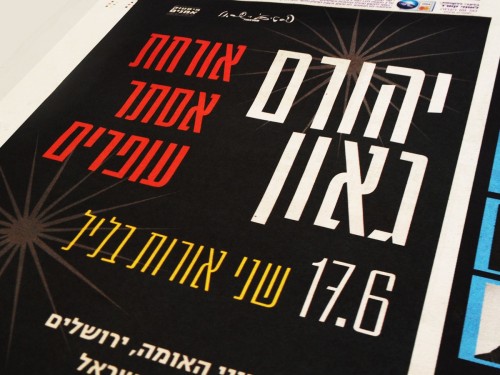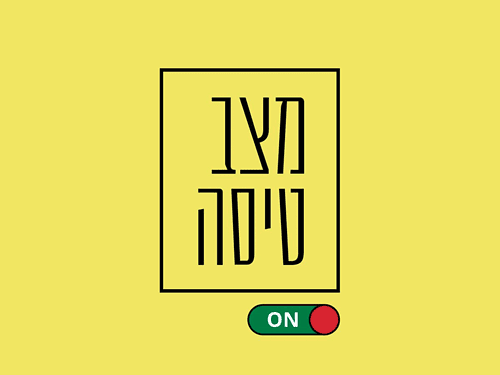
על אודות פונט בר־לב
פונט כותרת המשלב מבנה־אות גרוטסק עם אופי יציב ומוקפד, מה שהופך אותו לכלי אידיאלי ליצירת עיצובים מדויקים ובעלי נוכחות. הפונט כולל אותיות לטיניות ״גדולות״ (Uppercase), מה שמאפשר עבודה חלקה ואחידה בפרויקטים דו־לשוניים.
השראתו הסגנונית של בר־לב נובעת מגופנים ישראליים שהיו פופולריים בעולמות הפרסום והעיתונות בשנות ה־60 וה־70, מה שמעניק לו טאצ' נוסטלגי לצד רעננות עכשווית. התוצאה היא פונט המתאים במיוחד לכותרות בולטות, מיתוג וסביבות עיצוב דינמיות.
בתחילת שנת 2025, בר־לב התחדש בגרסה מעודכנת ומשופרת הכוללת שלושה משקלים חדשים (סה״כ 6), ניקוד מְתֻכְנָת, 151 תווים וסימנים חדשים (סה״כ 394), דיוק הפרופורציות והעיקולים של האותיות. בין החידושים ניתן להבחין באות ג׳ חדשה המציעה קריאוּת גבוהה המרחיבה את אפשרויות השימוש בפונט.
המלצת המערכת
עובד נהדר בכותרות מחאתיות ועצבניות.
המלצת שימוש לפי משקל
אולטרה־לייט לכותרות ענק
לייט עד אולטרה־בולד לכותרות ופסקאות גדולות -
- ליגטורות סודיות אשכרה ← אשכרה
- אל וגם ?! NO_
- חלופות סגנוניות #1 ג ← ג
- ₪ ← ₪
- ? ! ← ? !
- קֳ ← קֳ